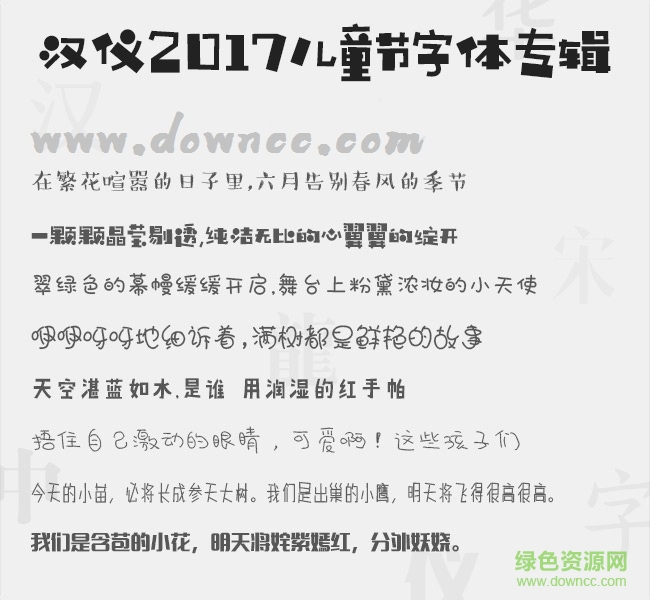
漢儀兒童節(jié)字體打包(共15款)
漢儀兒童節(jié)字體是一款漢儀類童年風(fēng)格字體,兒童體筆畫隨心所欲,字里行間透露的無憂無慮天真浪漫的可愛氣息,整體效果十分萌怪,還有更多類似好看字體歡迎來綠色資源網(wǎng)下載體驗(yàn)!
漢儀兒童節(jié)字體
該類字體粗細(xì)相間,字體筆畫隨意,其天真無邪的可愛風(fēng)格,非常有童趣,整體效果十分好看,感興趣的朋友歡迎免費(fèi)下載使用!